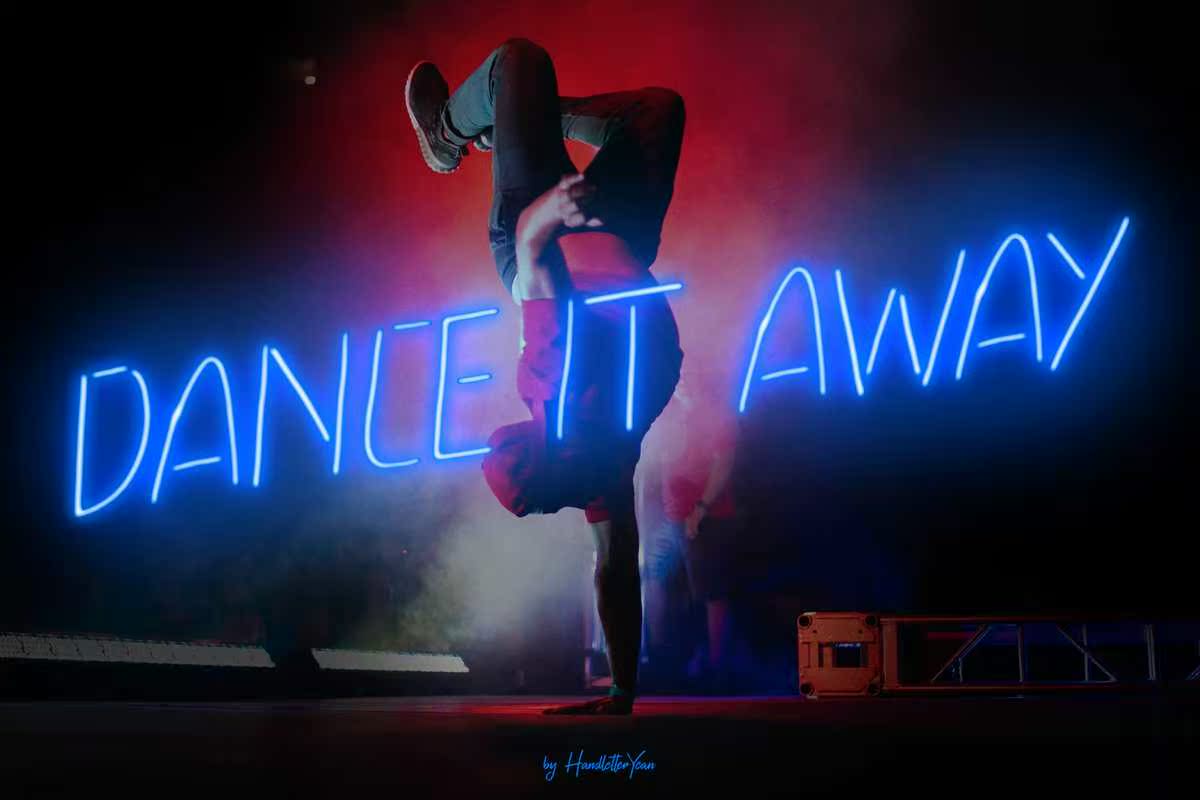
幸福之光经常以幻灯的形式出现。在感觉快乐之前,把你的身体移动到派对上,给你遇到的每个人一个最灿烂的微笑。用这个字体来分享你内心的幸福,因为这个字体看起来像包装、名片、邀请函、海报、标签,还有各种各样的设计。现在就开始吧。幸福之光常常以无数种灯光的形式聚集在一起。在感觉快乐之前,把你的身体移动到派对上,给你遇到的每个人一个最灿烂的微笑。用这种方式来分享你内心的幸福火花,比如包装、名片、邀请函、海报、标签和各种各样的设计。现在就开始吧。